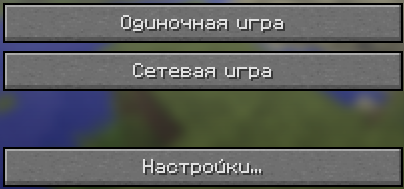
Какой шрифт вам больше нравится?
Mojang давно испортили | улучшили поменяли русские шрифты на новые, но до сих пор существует неопределенность по вопросу, какие же приятнее для глаз. Заранее благодарен за ваш голос!
1 вариант:
старый добрый шрифт со смайлами на "Ы" и "Ь" smile
2 вариант:
Новый лаконичный шрифт
Второй, потому что мне кажется он няяяшным <3
Лучше новый!!!
В первом много недочётов, а парой и багов
Тем более он выглядит красивее и делает Minecraft немного лучше
Мелочь, а приятно
А мне хотелось бы первый,но без смайлов.
Я бы оставил 1 т-к Minecraft является довольно архаичной игрой и шрифт должен быть соответствующим:громостким и квадратным
Мне больше 1 нрав)
ещё лутче, теперь я за третий ; )
Мне лично нравиться гораздо больше первый шрифт нежили второй!
Т.К. он больше подходит к тематике minecraft'a...
и просто он красивый)
Только 1,только хардкор !!!
В идеале вообще HD шрифты, которые с текстурпаками идут...
А так 1-ый, только если без смайлов.
1. Он лучше читается, т.к. он больше
2. В чате в мультиплеере если нет русификатора, будет всякая шняга
3. Удобнее, опять же по своему размеру
4. Он более "кубический", что подходит под стиль майна
...
over9000. ХАРДКООООР
Первый лучше несомненно, к нему уже все привыкли. Он такой же квадратный как и сам Minecraft, свой голос отдаю первому!
1 самый удобный и нормальный 2 полное уг и для глаз неприятен fellow
1 Мне он больше по душе
1ый зэ бэст!
1 ваще крутой я к нему привык а 2 полная,уналая фигня!
2 шрифт у меня вызывает чувство паники, так и хочется сразу же на английский язык переключиться. Бр... Терпеть его не могу. ИМХО
Я думаю что первый он толще. smile
Мне 1 понравился, потому-что 2 мелкий и некрасивый.
В чём проблема? Найти в джаре эту картинку со шрифтом и по примеру с других букв нарисовать Ы и Ь. fellow
Обожаю первый шрифт!Всё в нём хорошо,но портят смайлики...
Отдаю голос за 1 вариант!
Отдаю голос за второй. Первый выглядит лучше, но бесят смайлы и то, что сделан он через одно место. Тем более со вторым шрифтом можно выбрать любой язык игры, а первый показывает только английский. Ещё со вторым РАБОТАЕТ такая мелочь, как поиск предметов в креативе.
Мне нравится что-то среднее между первым и вторым. Первый слишком громосткий, а второй слишком тонкий. Вот такой тупик.
Отдаю голос за первый ,первый шрифт более привычен ибо этот шрифт сопровождает нас с начальных версий майнкрафта. Первый шрифт Forever!!!
И все таки первый шрифт вызывает какие-то ностальгические чувства.Заставляет вспомнить тот момент,когда ты поставил в первый раз тот русификатор,являясь ещё не совсем опытным игроком и увидеть игру совершенно другими глазами,почувствовать всю прелесть русского общения на серверах...вот все же мелочь,а без него уже не то.